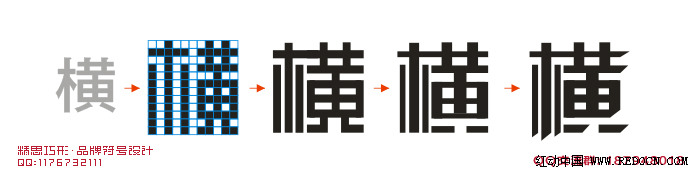
字体设计方法——笔画方直
字本身笔画的分布决定了字体的重心及识别性,当然也包括美感,一旦字的重心(上下)和中线(左右)变化不一致,字体肯定不好看。所以,我想我们训练的方式也得调整下,我看了下前面总结的《文字符号设计方法--笔画字形(体)设计方法大纲》里的20多种笔画字形的处理手法,发现有的方法本身就对字体特征的把握有帮助,所以,得重新调整顺序,最先做“方直化”的笔画练习,这对字体结构的调整及美感把控有帮助,后面再练较复杂的笔画变化处理方法。
笔画方直(方正化)
这种处理手法,就是把笔画全部都尽量方正,横平竖直,撇捺都变成直角,这类字体基本都是以等线体(横竖一样粗)为基础的,当我们把笔画全部横平竖直处理时,字的笔画结构就清晰简单了,我们在不断调整横竖位置的过程中,可以加深对字体结构的把握能力。
为了便于把握,我们做字体设计时,都是以黑体,等线体,综艺体等这类笔画平直的字体做为变形的基础,要么就是先横平竖直的把字体笔画写出来,所以这个手法最贴合基础,可以看上图里的“家”字,撇 弯钩都变成了直角折笔,如果我们将所有笔画都方直化,那么为了让字保持均衡,就需要上下左右的移动调整笔画,这个过程就比调整弯曲的撇捺位置,要容易的多。
对于初学者和字体美观把握不够的人而言,先练习这种手法最合适,做这种练习的步骤, 就是 《汉字结构特征的把握》 文章里罗列的,笔画调整,缩放调整,重心调整,平衡调整,笔画穿插调整等等,我在后面的视频里也说了,现在用文字大概说一下顺序:
1)打辅助线,做出字体的外轮廓线,田字格,米字格都行。
2)依据基本字体(比如黑体),将文字的笔画处理的衡平竖直(方直化),横竖笔画可以先一样粗细。
3)依据辅助轮廓线,对字进行 视觉面积(缩放)调整,尽量使文字笔画充满轮廓四周和四角。比如上图的字,“雀”和“台”的上面竖笔可以冲出轮廓外框,从而保证三个字的视觉面积相近, 具体的“缩放调整”请参看《汉字结构特征的把握》 文章里的说明。
4)依据基本字形部首比例,调整部首比例关系,以确保字体美观。
5)调整字体的横笔和竖笔,确保字体视觉重心一致。 横竖笔画决定了字体重心的高低和左右,所以能统一高度就尽量统一高度。将这组字的视觉重心控制在一样的位置。因为这里的“台”字笔画简单,为了保证视觉面积上大小一致,这类稍调窄些。
我们最终就是要下面的结果,就如同放在田字格里,视觉重心都调整到一致。
这是最简单的练习字体设计的步骤,在我们不断做这种方直化的基础练习时,对字体的笔画结构,部首比例,重心位置,都会越来越敏感,这就是字体美感的把控。对于字体把控能力较弱的人,一定要多做此练习,这也是我们后面字体设计处理方法的基础,我们要求,后面的笔画字形的处理方法训练作业,上来都要先将“作业题”的文字这个方直化的处理,然后才做后面的比如“连笔处理”“折笔圆滑”等。 我们先不要求使用现成的字库字体,什么字都要自己先做方直化处理,这样可以强化字体美感把控,几节课下来就把握住了。
一般的字,横笔竖笔不会太多,横细一致的话,放到网格里,加上间距也就9到12格之间,比如下面的“横”字。就像素点化一样,一旦方直化后,再调整笔画粗细,做笔画其他效果的处理就能保证字体结构的稳定了。
如果做辅助线,也可以依据上图的网格来做,我们用钢笔(路径)打字体结构,也就是横竖的粗细一致,如果字的横笔或竖笔很多很密,那就把不重要的笔画变细,来保证字体的协调,然后再做笔画的处理就容易了。
上图中的网格也是像素化字体的设计方法,这种模仿像素点的手法,也属于笔化方直的延展,都比较适合刚开始练习字体设计的朋友,如下图:
这种像素化的处理手法,可以通过打网格做出,也可以通过PS里缩小放大字体像素得到,还可以模糊后,使用滤镜里的像素化里的效果得到,如果再结合字体本身结构的上的处理,效果更好些。如上图的苹果地带,笔画粗细长短不一致,结合像素化效果。
即使是简单的横竖,相对于一个字的结构还是有很多处理手法的,如上图中的“心”字,写法很多不同,但我们还是能够识别出这个字,一旦基础形态决定了,再改变笔画笔触,不论是圆角还是斜切,基本不会影响这个字的结构。
横笔的上下调整,是在调整字的重心高低。竖笔的左右调整,决定了字体的重心偏移,所以,横竖的笔画调整,最直接最容易把握。基础字形做好后,在调整笔画,比如把横笔统一变细,把折笔处统一变弯,就可以做出更多效果的字体了,所以应该说方直化是字体设计基础。
很多模仿古体篆书的字体设计,经常用到,也就是我们上次总结的笔画回折。如下图:
篆书笔画结构复杂,多直角曲折,所以很容易处理。仿篆书的方直化处理难点有:
1)连笔穿插。这类字体设计喜欢通过一笔链接,来使字体笔画繁多的篆书看起来流程,如上图的中国智宝,里面的口日贝,都破开一笔贯穿的,还有上图左下角的“丰源”,源字,基本也是通过笔画的链接处理来简化的,而且这类字体多加边框模仿篆刻印章,笔画之间的间距基本一样,像是迷宫。这里面的笔画与笔画如何穿插与避让,能保证字的结构特征还能识别出来就是个难题。但是多收集些前辈们做的这类字体,看看他们同类“部首”的处理方式,就能总结出规律,比如,单人旁、三点水,心字底,贝字,女字,等这类笔画如何处理的,看几个心里就有数了。
2)笔画回折。很多字笔画多少不一,为了充满空间,需要笔画回折。(所以我一开把它们归在笔画回折里,但是整体的思路也是从笔画方直延展过来的。)如果是简体字,笔画简单,如上图的“春江花月”,就要考虑如何回折笔画,来填满空间。这里的花与月的最后一笔,都是在呼应前面的春的“日”字的处理方式。回折类似回纹,只要在字的某个范围内,多回转几圈,也不影响字体结构。
总之,笔画方直,是变化字体的基础,容易把握字体结构,放在前面训练比较好,至于像素化,和篆书回纹都是一样的思维方式和处理方法。只要笔画结构布局合理,看起来美观了,后面怎么添加变化都行。